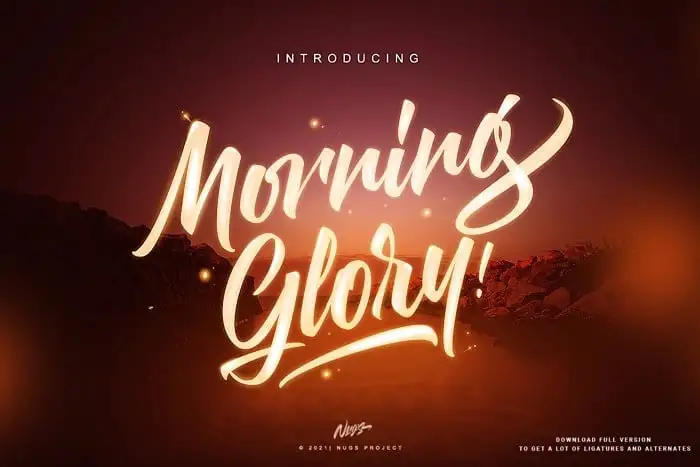
Morning Glory Bold Script Font – Download Grátis
A Morning Glory Bold Script Font é uma criação elegante e delicada desenvolvida pelo designer Nug’s Project. Este tipo de letra é perfeito para diversos fins criativos, desde os títulos até as etiquetas dos produtos, passando por ombros de carta, selos, cartazes, adesivos e outros designs que precisam de uma fonte única e chamativa. Seu estilo dinâmico e energético faz dela uma opção perfeita para qualquer projeto gráfico que busque trazer destaque à sua arte ou produto. Com seu design bold e sofisticado, você pode expressar personalidade em suas criações, tornando-as ainda mais memoráveis. A Morning Glory Bold Script Font é um presente para designers buscando uma fonte de script com a intensidade certa para destacar seus trabalhos.